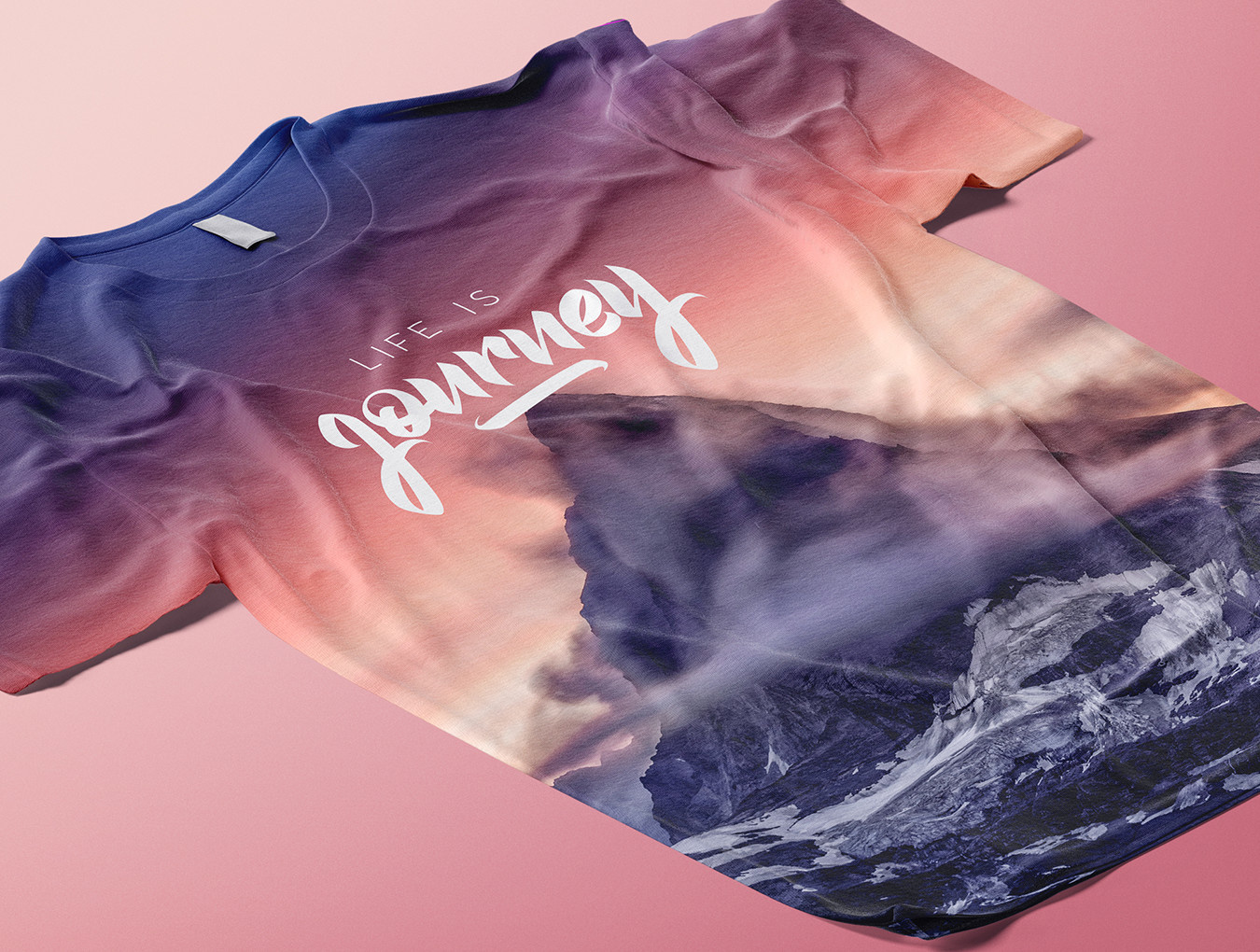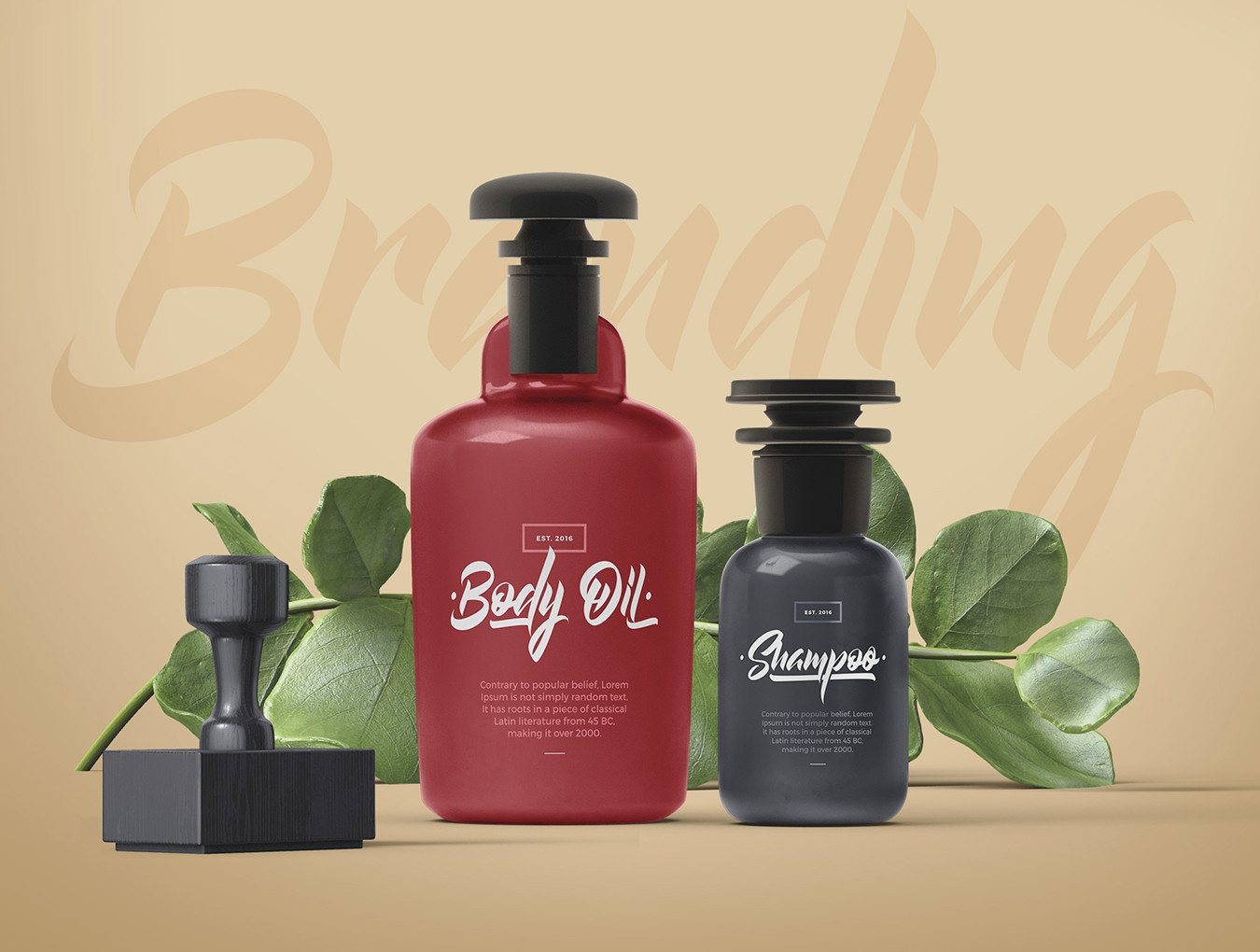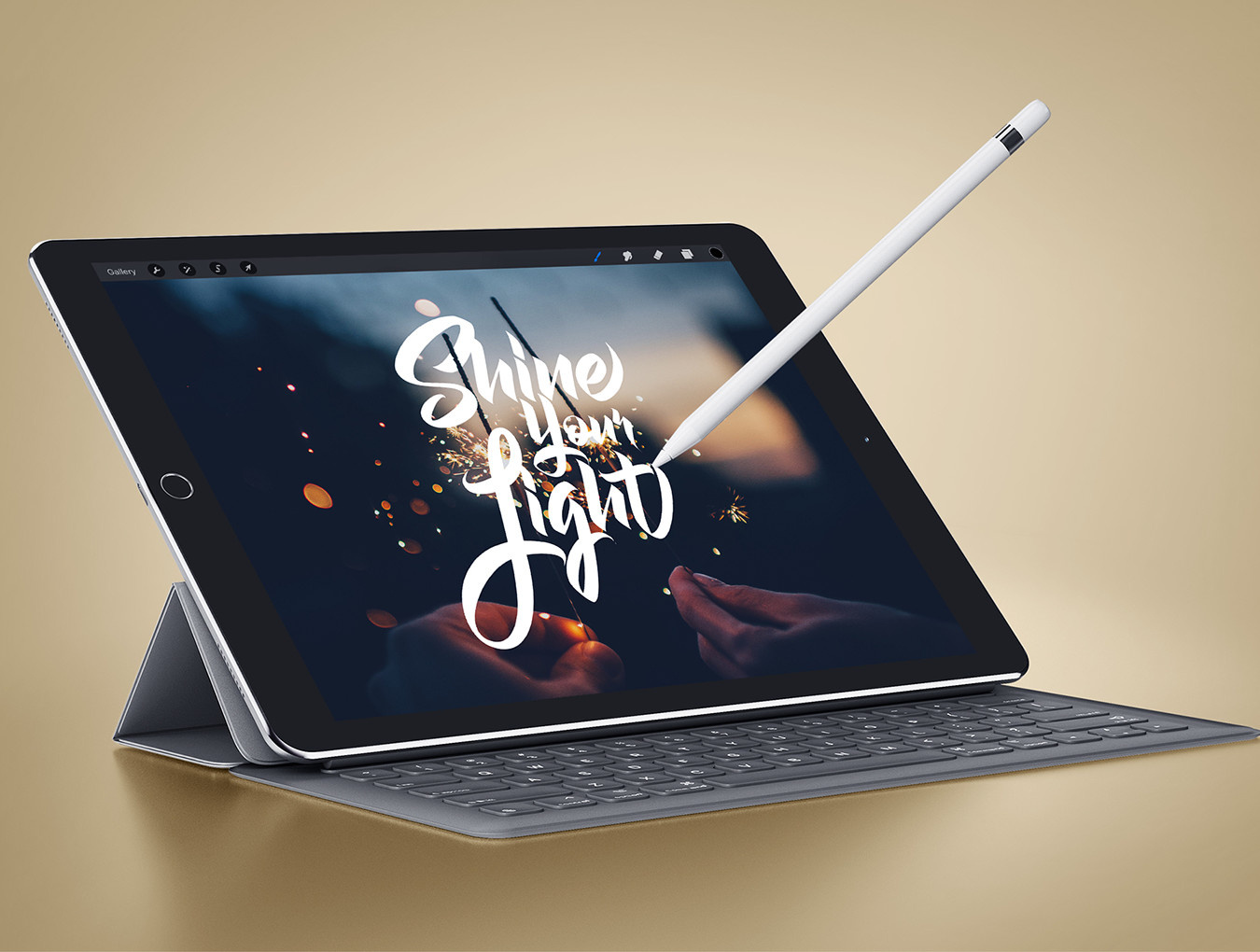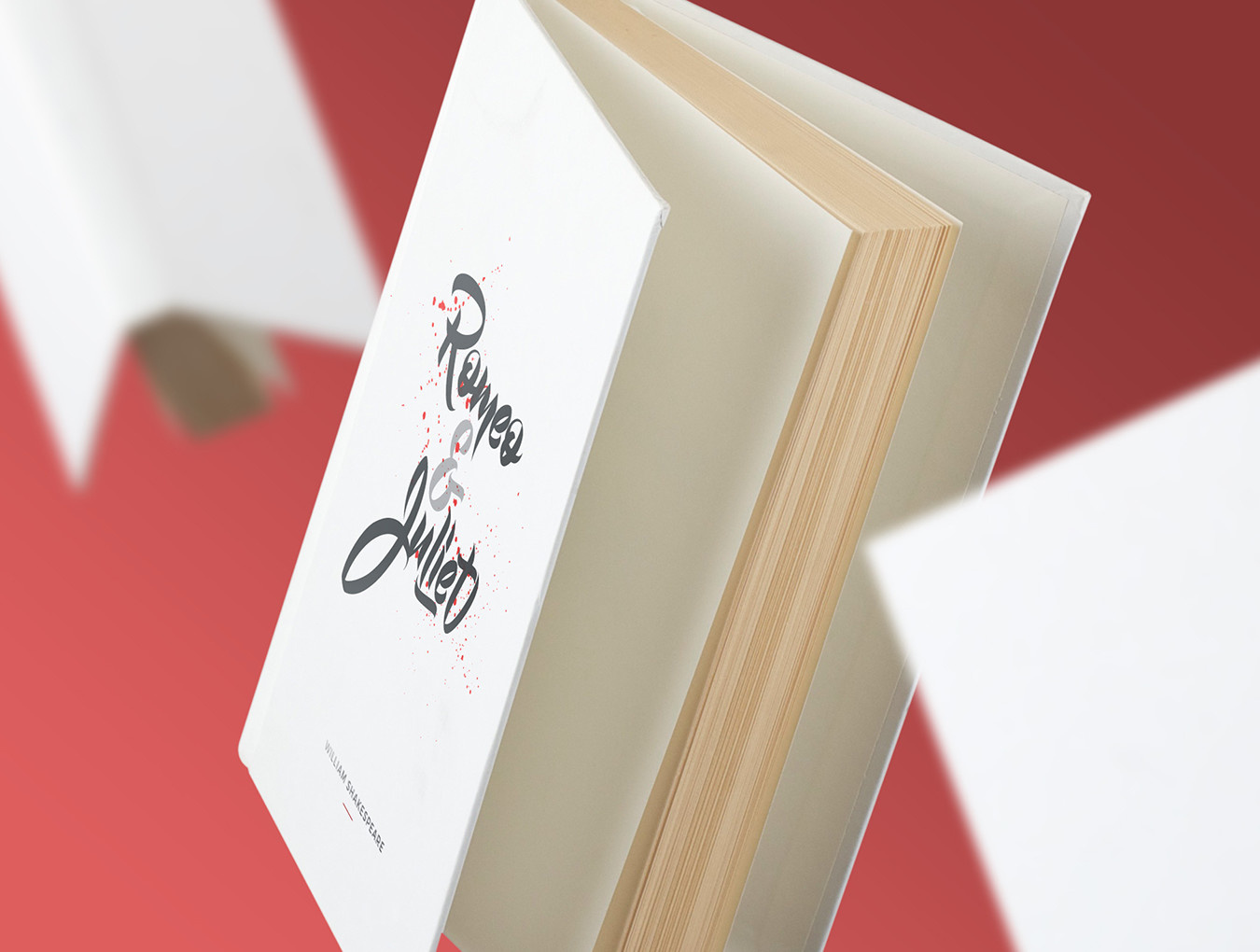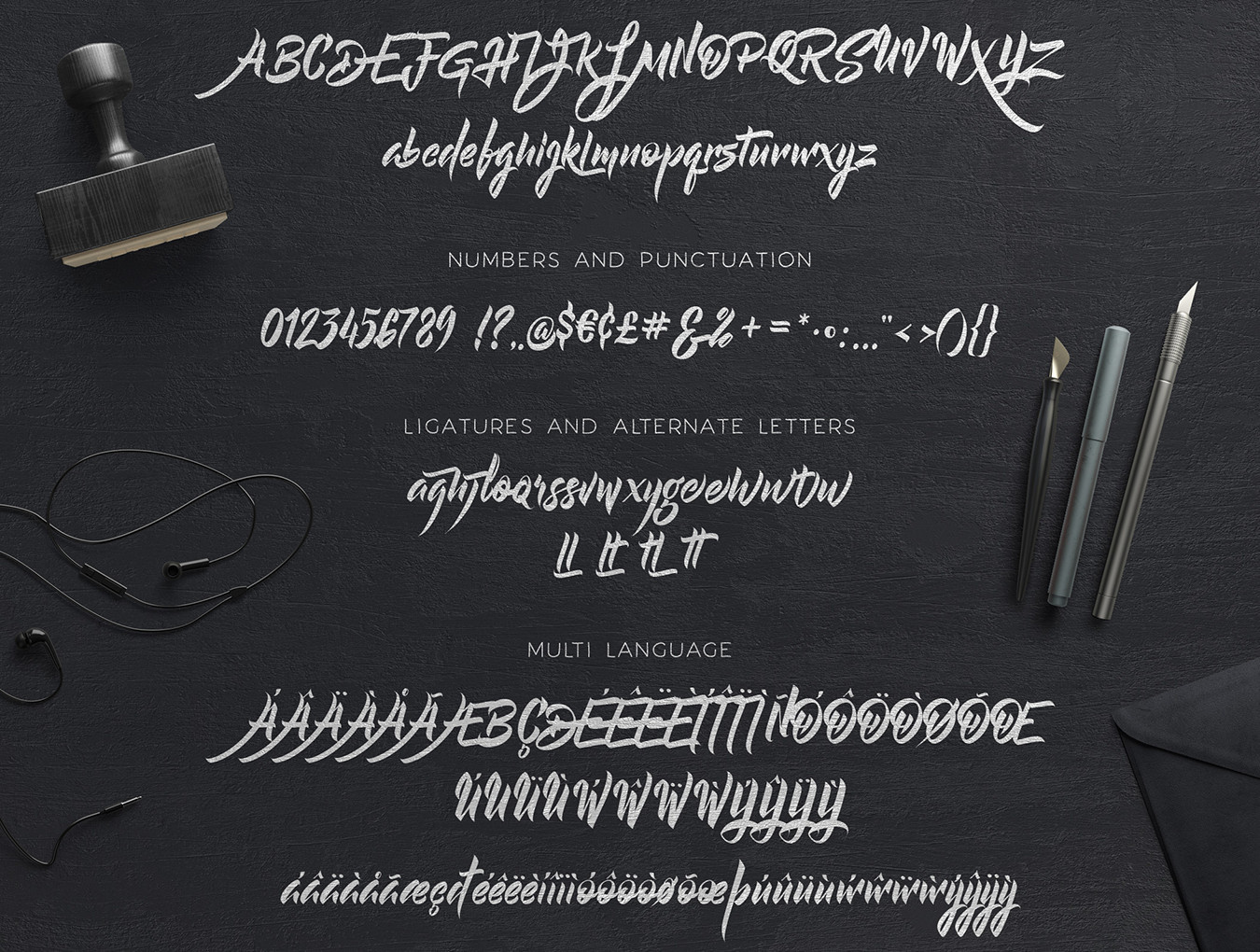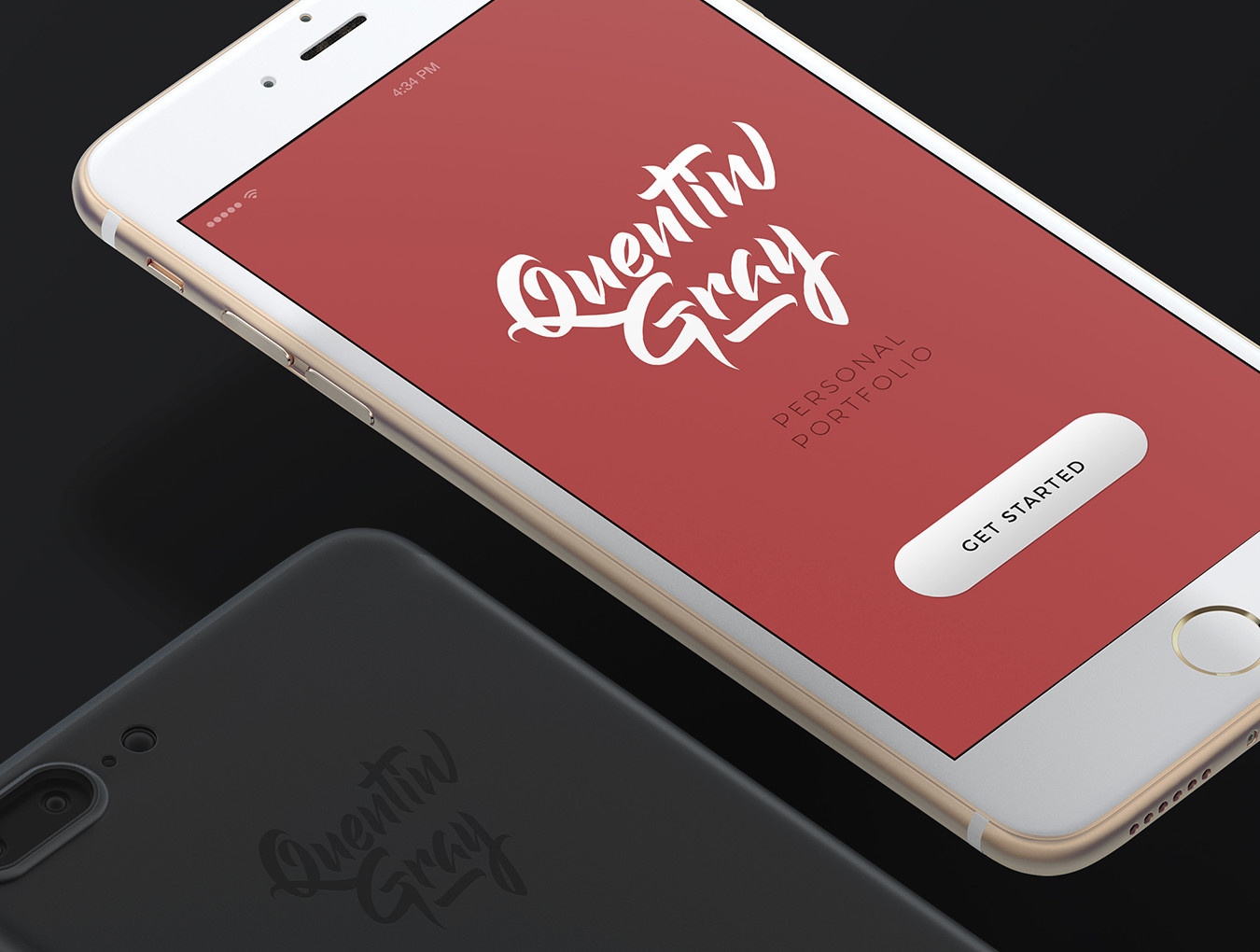
完美的刷字体 - 只为你!,Leviafan字体
Perfect brush font - just for you!, Leviafan Font
Leviafan是一种带有画笔风格的手绘字体,非常适合信头,服装设计,标题,标识,海报,卡片等。对于拥有opentype软件的人来说:通过打开'Stylistic Alternates'和'可以访问替代品Photoshop的“角色”面板中的“连结”按钮,或者通过任何带有字形面板的软件,例如Adobe Illustrator,Photoshop,Inkscape。